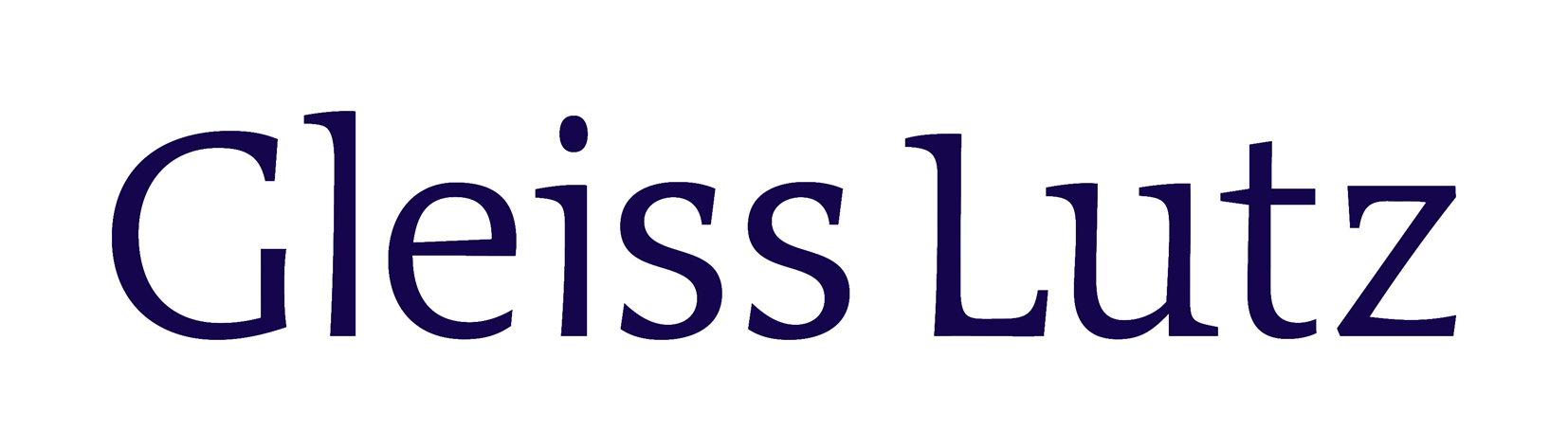
Logo: Schrift für einen Rechtsanwalt
ich bin auf der Suche nach einer Schriftart für einen Rechtsanwalt. Das Logo soll letztlich nur aus einem farbigen Namensschriftzug bestehen.
Beispiele:
Gleiss Lutz
Wildanger:
Übersicht anderer:
Die Schriftart soll klassisch, konservativ und seriös sein, aber trotzdem zukunftsorientiert wirken. Der Kanzleiname ist übrigens sehr kurz; nur 4 Buchstaben. Es ist wohl beabsichtigt im Briefkopf sonst Times New Roman zu verwenden (nicht zwingend).
Puh – da geht sehr viel. Kommt auch etwas auf die Buchstaben an. Sind das alles Versalien?
Spontan erstmal Richler oder eine aus den Listen von Kathrin, Ralf und mir:
Die Art der Schreibweise ist mir überlassen. Bisher werden Kapitälchen verwendet. Wollte diese wahrscheinlich beibehalten.
Wenn die Times New Roman für den Briefkopftext verwendet wird, kann der Firmenschriftzug nicht gut in einer ähnlichen Schrift stehen. Das wäre ein programmierter Unfall. Der Briefbogenentwurf* ist Bestandteil der Aufgabe, sonst wird es am Ende ziemlich sicher böse aussehen.
* Ergänzung: inklusive Brieftext
»Die Schriftart soll klassisch, konservativ und seriös sein, aber trotzdem zukunftsorientiert wirken.«
So definiert man Widersprüche. Die Wortfügung »aber trotzdem« gibt einen guten Hinweis auf unerfüllbare Wünsche. Der Begriff »zukunftsorientiert« wird wohl kaum zu definieren sein, auch eine solche Wirkung kann ich mir nicht vorstellen. Es geht vermutlich eher um die Gegenwart.
Falls Englischkenntnisse vorhanden sind, empfehle ich von Matthew Butterick, Rechtsanwalt und Grafikdesigner mit typographischem Schwerpunkt, für eine umfassendere Annäherung an das Thema:
sowie
Naturgemäß geht Butterick schwerpunktmäßig auf US-amerikanische, zum Teil recht rigide Anforderungen ein, ein Teil der Aussagen ist aber auch für hiesige Verhältnisse beachtenswert, und sei es in Übertragung – so z.B., warum man seines Erachtens keinesfalls Times NR benutzen sollte, angesichts besserer Alternativen (http://typographyforlawyers.com/system-fonts.html und anderenorts).
Abgeshen von den von ihm gegebenen Hinweisen, die auch Empfehlungen von Fonts anderer Anbieter umfassen, bietet er selbst die von ihm speziell im Blick auf den Bedarf von Anwaltskanzleien konzipierten Schriften Equity (ähnlich der Ehrhardt) und Concourse (eine geometrische Sans) an, unter den Links jeweils mit umfangreicher Muster-pdf, wobei ich mit diesen Schriften allerdings keine Erfahrungen habe.
Für Juristen: Equity + Concourse
Die Serifenschrift Equity und ihre serifenlose Schwester Concourse wurden 2011, bzw. 2012, speziell für die Bedürfnisse der Verfasser juristischer Texte von Schriftgestalter Matthew Butterick entworfen.